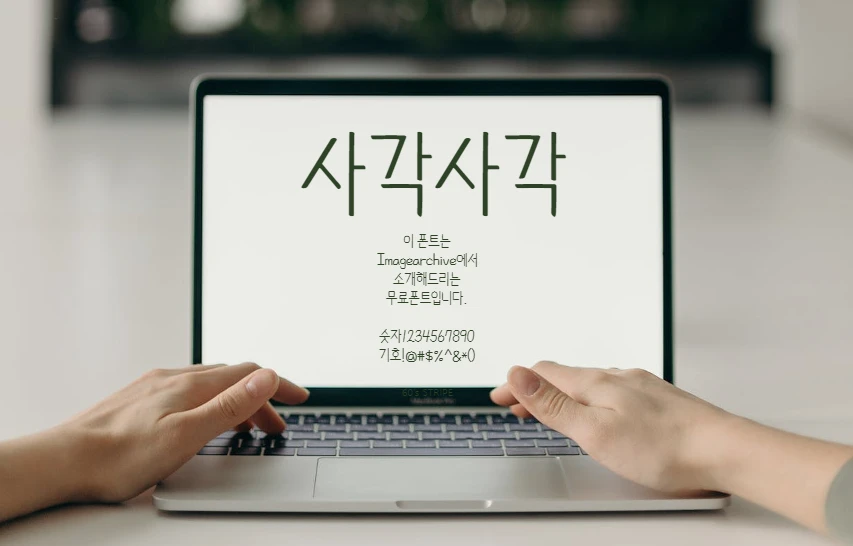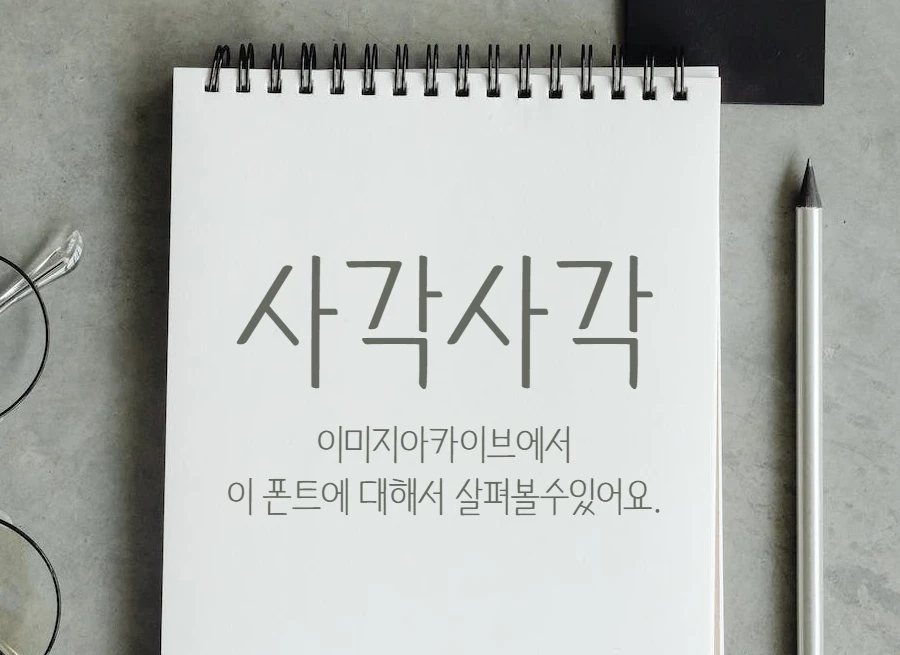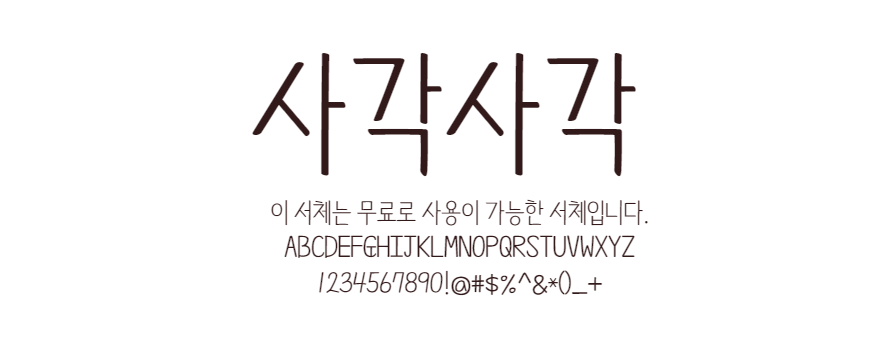
사각사각
제 손글씨를 바탕으로 만든 손글씨 폰트입니다. 매일 샤프로 일기를 쓰면서 저의 또다른 손글씨도 폰트로 만들어보면 재밌겠다는 생각이 들었습니다. 그래서 이 폰트의 이름을 '사각사각'으로 지었습니다. 이는 샤프로 글씨를 쓸 때 나는 사각거리는 소리를 담고 싶었기 때문입니다. 작업은 2023년 10월 28일부터 시작하여 2024년 1월 20일에 1차 완결을 보았습니다.
사용한 프로그램은 Fontcreator이며, 비용을 지불하고 정품 라이센스로 사용했습니다. 작업 과정에서는 휴먼범석체 파일을 바탕으로 각 글리프를 수정했습니다. 참고로 휴먼범석체는 OFL인 네이버 나눔고딕체를 이용하여 만들어졌습니다.
이 폰트는 상용한글 2350자+a와 영어 대/소문자, 숫자 및 특수문자, 라틴어, 그리스어를 제공합니다. 일부 기호도 제작해 두었습니다. 한글로 만들어낼 수 있는 모든 글자는 11172자로, 이를 '현대한글'이라고 부르며 여기에는 '뭵', '삂'과 같은 글자들이 포함됩니다. 작업한 내용 이외의 글리프들은 기본 글꼴로 표시됩니다.